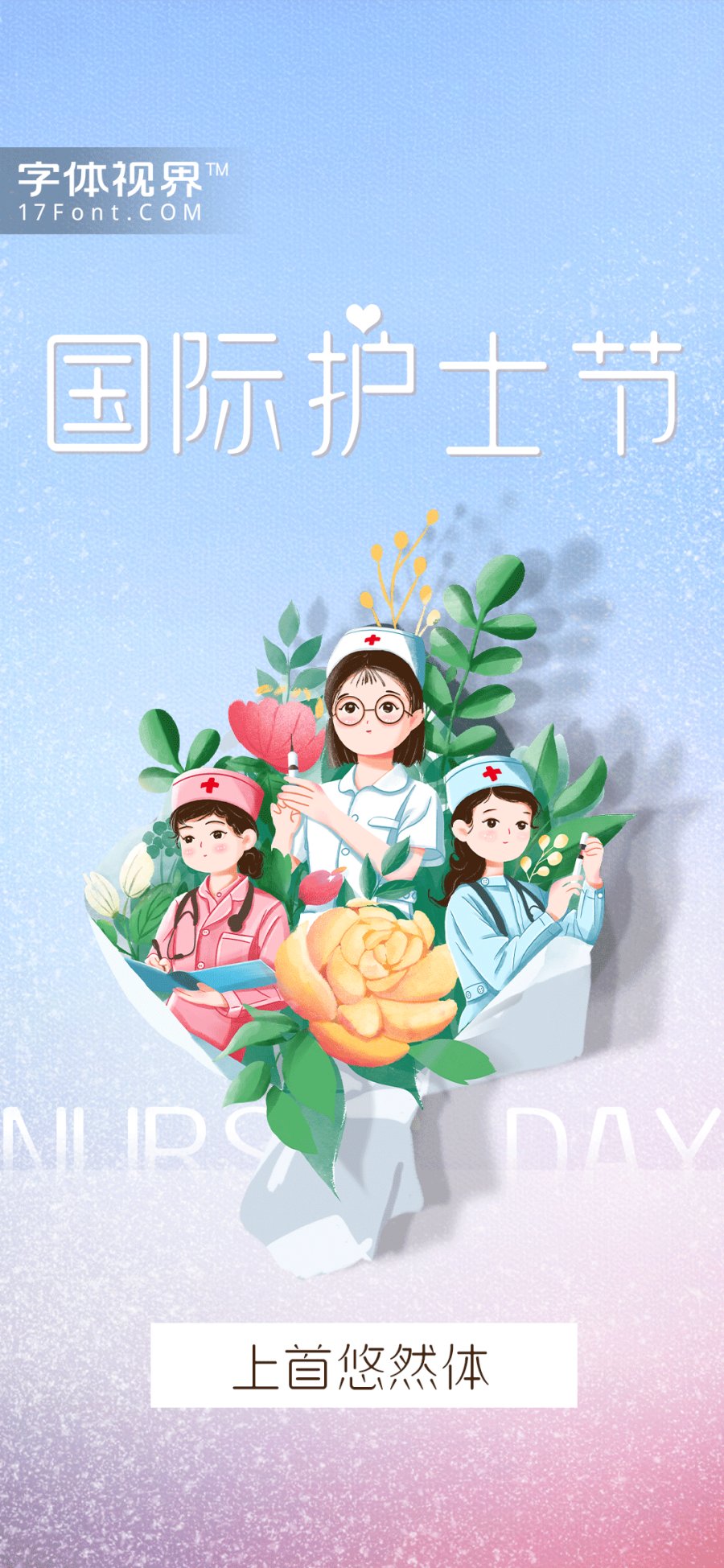
白衣天使就像一台不屈不挠的机器,把无数的病人从死亡之手带回来,总是让人感动不已。每年的5月12日是国际护士节,赞扬护士们不畏艰险、甘于奉献、救死扶伤、勇于献身的人道主义精神。护士节到了,让我们用上首悠然体致敬白衣天使,祝愿白衣天使节日快乐。
上首悠然体字体笔触纤细,字形端正,字形优美,如山中清风、溪中流水,给人们一种新颖、时尚、优雅,秀丽和轻盈感。目前上首悠然体已经在字体视界上线,平台已经取得该字体的官方代理授权,有权为您提供字体授权服务。